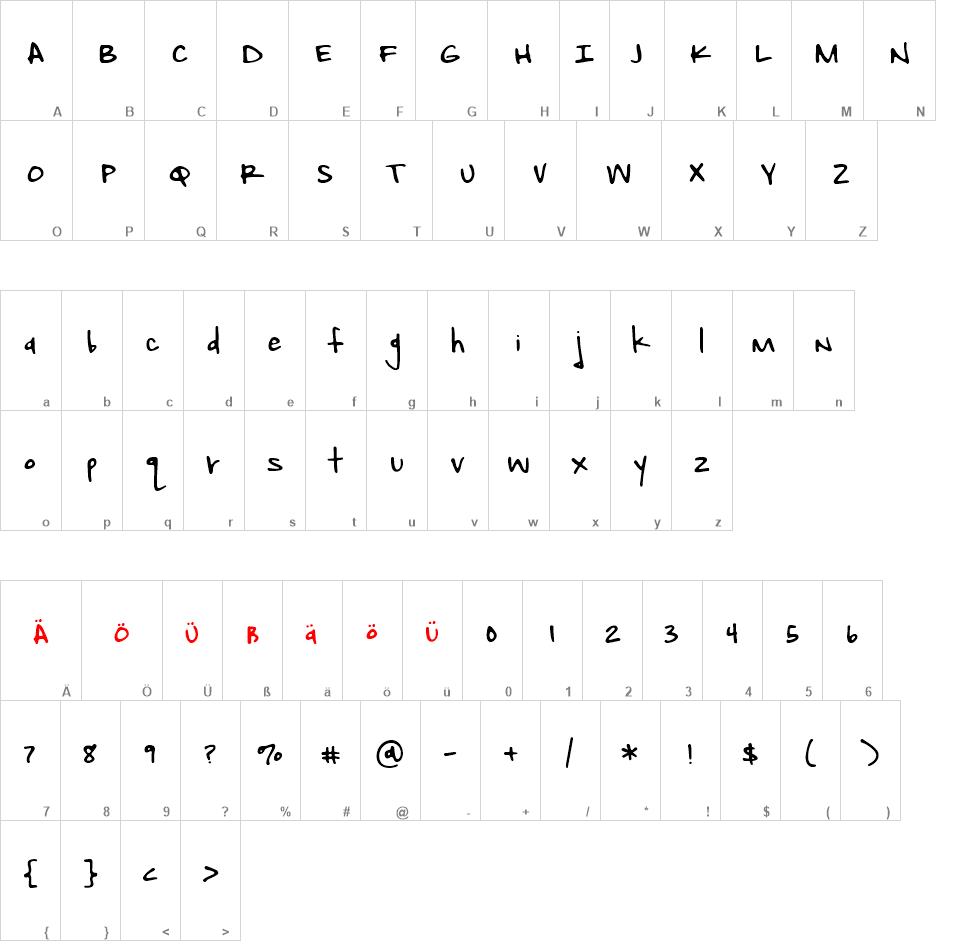
Ambition & Ink
Ambition & Ink font
Ambition & Ink
Ambition & Ink ist eine driven handdrawn Schrift. Es kann leicht als eine Unicase-Schriftart verwendet werden, indem die Kleinbuchstaben, die Ober- und Unterlängen (bdfghjklpqty) für Großbuchstaben haben, mit Subbing versehen werden.
Die Schriftart hat 546 Zeichen, darunter viele Buchstaben mit Akzenten sowie Griechisch und Kyrillisch.